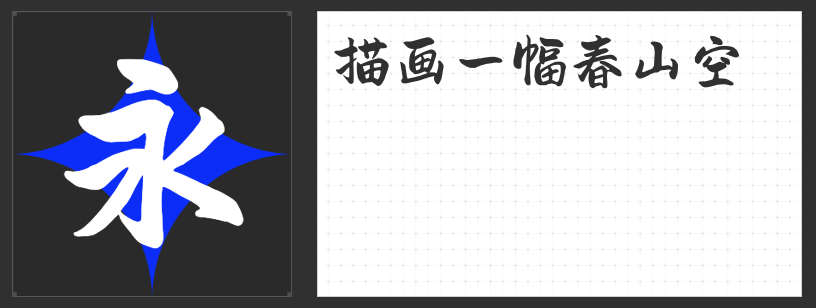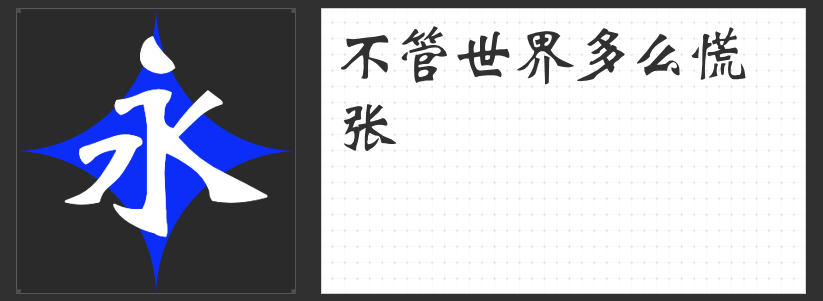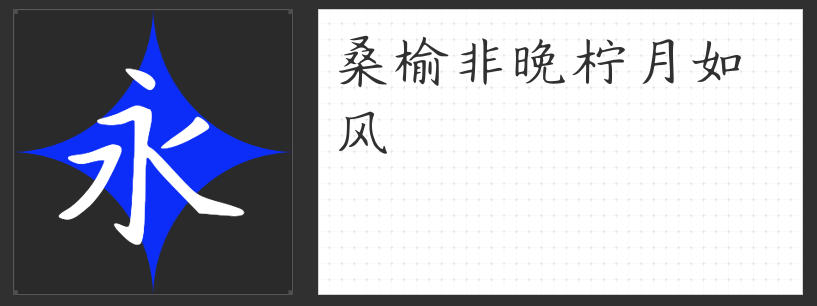
四款复古风字体:解锁怀旧设计的视觉密码
在复古与怀旧风格设计中,字体的选择是奠定基调的核心要素。以下四款兼具艺术价值与历史厚重感的字体,以独特的笔法结构与文化内涵,为设计注入跨越时空的美学张力。
一、云书法三行魏碑体
这款字体脱胎于北魏碑刻的浑厚气韵,将隶书蚕头燕尾的舒展与楷书严谨的结体相融合。其笔画粗重饱满,横捺延展至字形边界,撇捺收笔处的粗钝处理形成动态张力,既保留了魏碑“朴拙险峻”的原始美感,又通过现代设计手法强化了视觉冲击力。工整的楷书框架下,隐含着隶书向楷书过渡的历史痕迹,适用于需要营造庄重古雅氛围的标题与正文设计。
二、励字舒体简繁
此字体以“师古而不泥古”为设计理念,在楷书骨架中融入行书的流动感、隶书的波磔、草书的恣意与篆书的圆劲。字形结构上,颜真卿的雄浑与柳公权的骨力相互渗透,形成“弯弓盘马”的视觉张力。笔画转折处既有金石刻画的刚劲,又暗含毛笔书写的柔韧,尤其适合需要传递文化底蕴与艺术创新双重特质的品牌视觉系统。
三、励字魏体简繁
设计师将龙门二十品的方峻笔法转化为印刷体语言,通过“点画精致、刚劲有力”的刀刻痕迹,重构魏碑的雄强气质。收笔方圆兼施的细节处理,既保留了北魏造像题记的原始质感,又通过标准化设计提升了字体的适用性。齐正相生的结构布局与轻重交错的行笔节奏,使其成为兼具历史厚重感与现代设计感的标题字体首选。
四、造字侠陈坤风行简繁
这款字体以“笔画窈窕、结构洒脱”为特征,在保持书法字形的自然书写感同时,通过圆融用笔与点睛笔画的设计,赋予每个字符独特的生命力。其结构摆脱了传统印刷体的机械感,笔画间的呼应关系暗合文人书法的气韵流动,特别适合需要营造轻松雅致氛围的复古海报与品牌标识设计。
四款字体分别从北魏碑刻、文人书法、刀刻美学等维度切入,通过现代设计语言重构传统字形的视觉价值。设计师可根据具体场景需求,选择与之匹配的字体来传递历史温度与艺术创新并重的视觉语言。